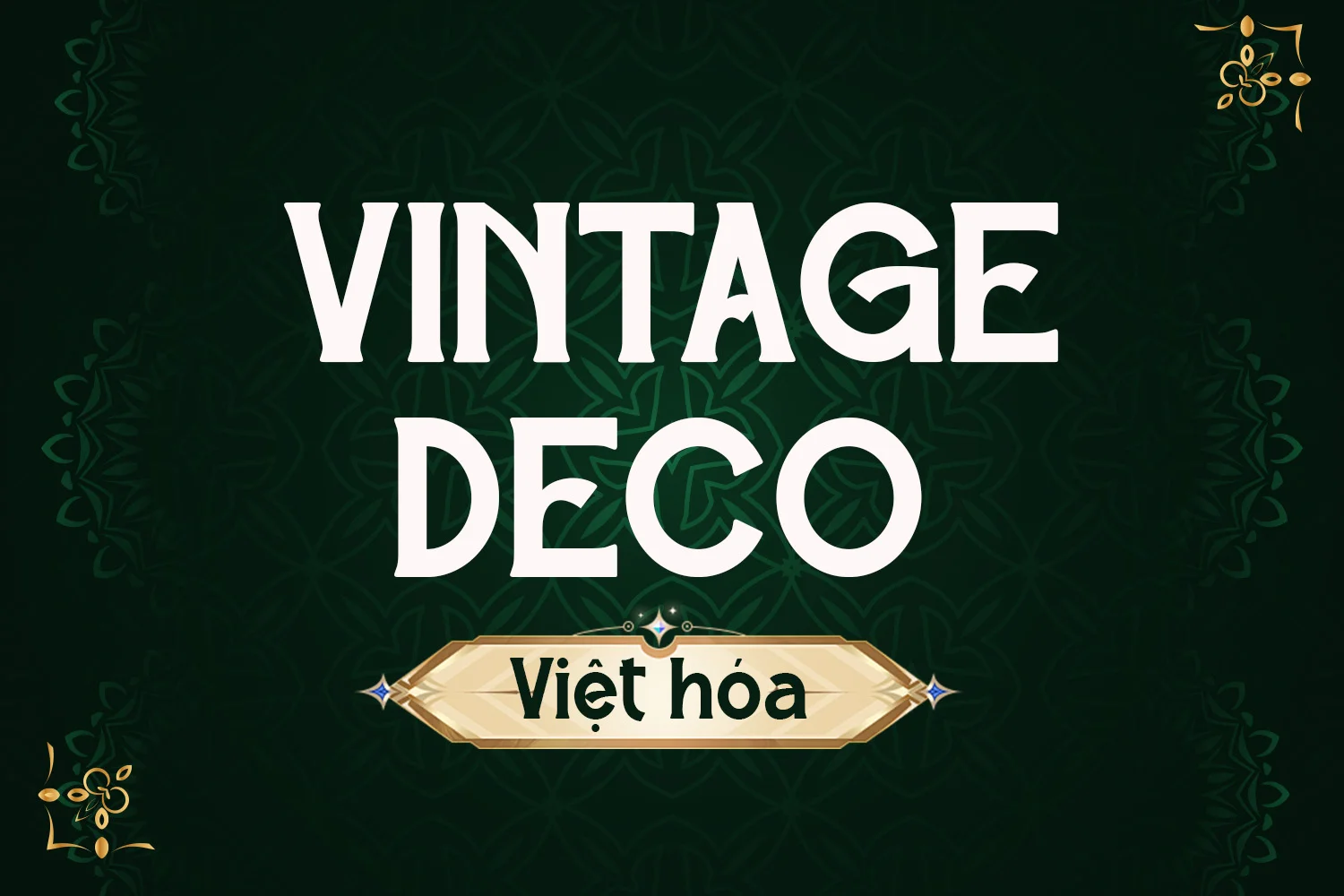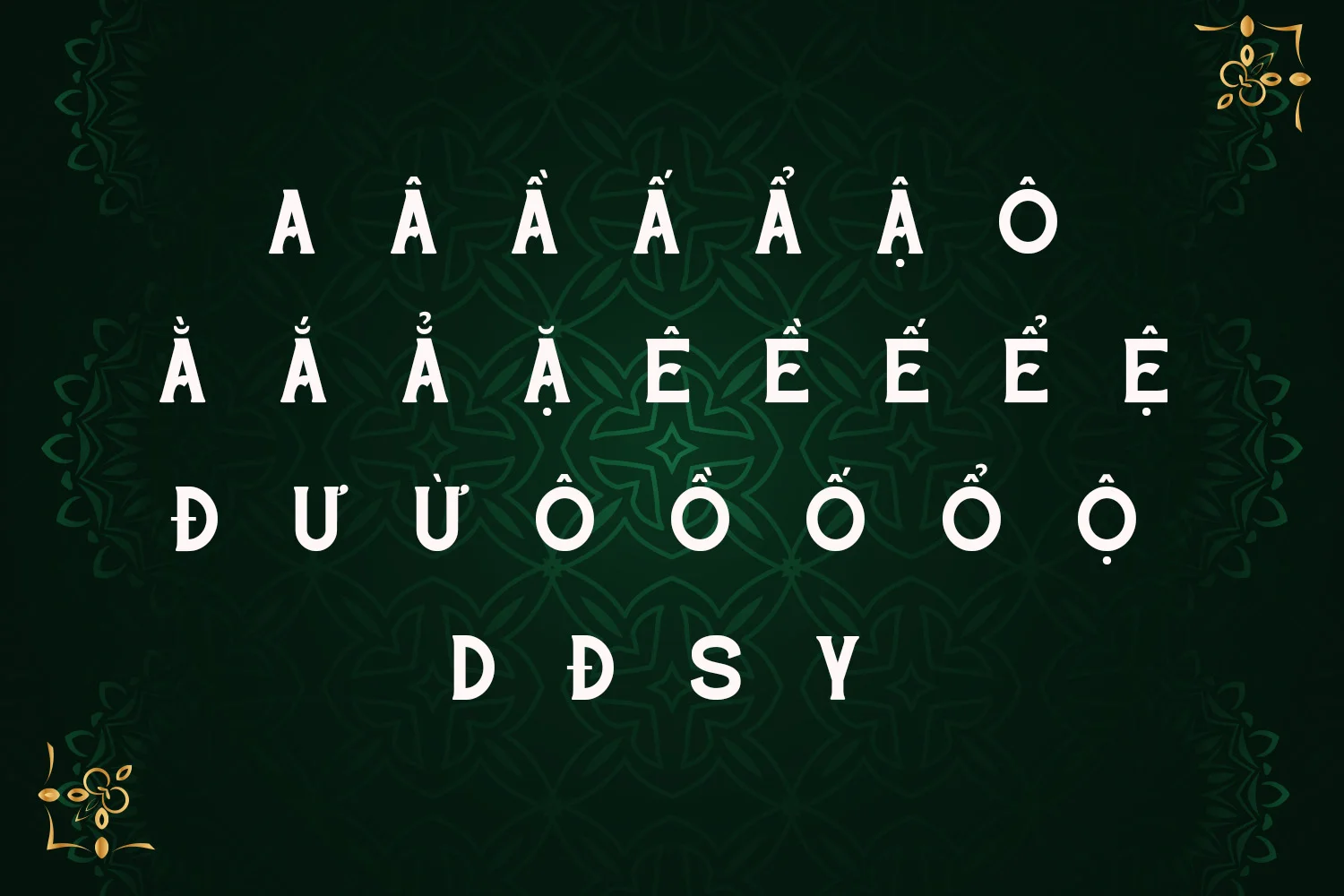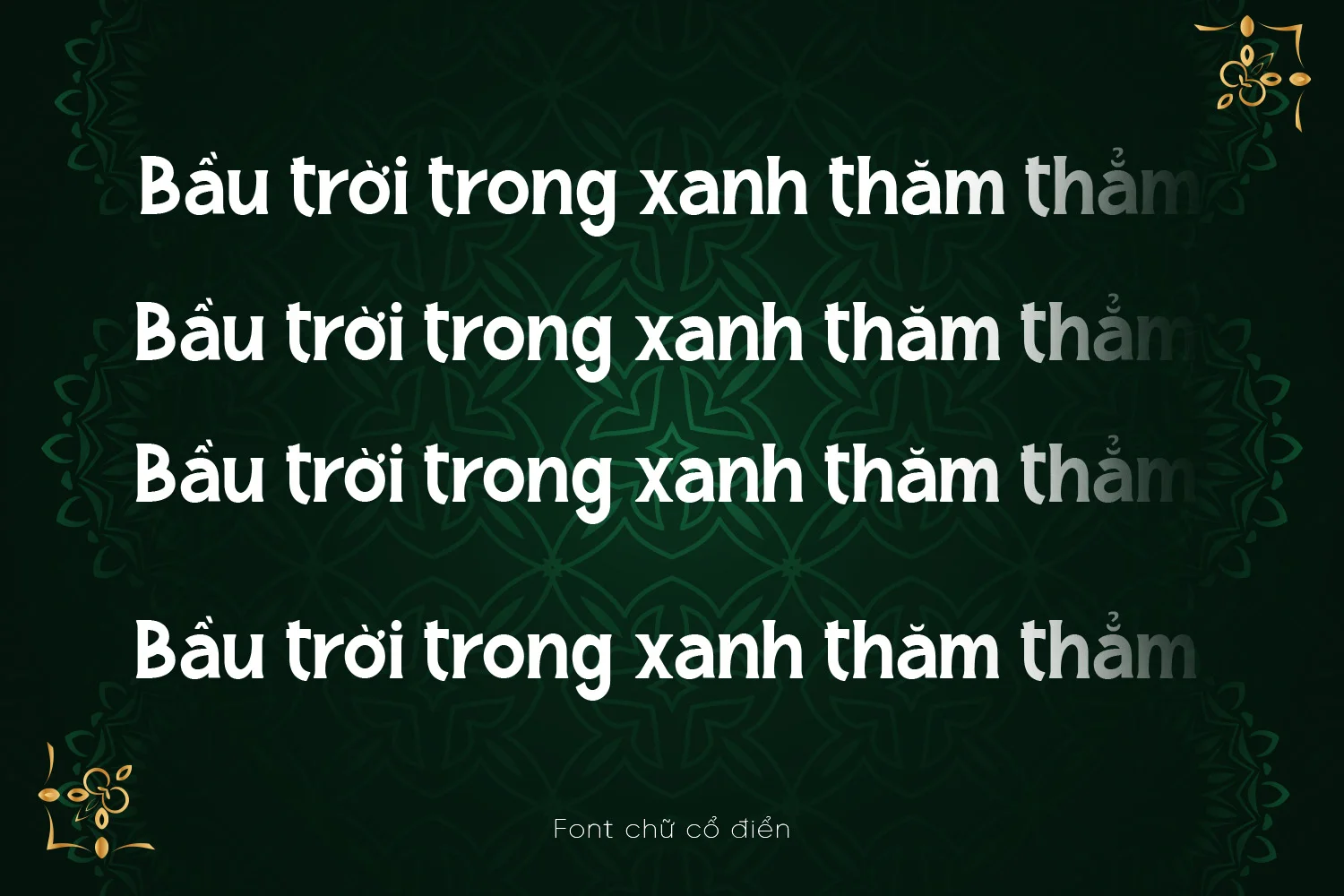
DVN Vintage Deco Việt hóa là kiểu chữ mang đậm hơi thở hoài cổ, gợi nhớ về thời đại vàng son của thiết kế Art Deco. Font sở hữu các nét cắt hình khối rõ ràng, kết hợp cùng các chi tiết trang trí tinh xảo, tạo nên cảm giác sang trọng và nổi bật. Ngoài bộ ký tự tiêu chuẩn, font còn tích hợp các ligature và ký tự thay thế độc đáo giúp bạn thoải mái sáng tạo. Bộ font hỗ trợ tiếng Việt đầy đủ và tương thích tốt trong nhiều ứng dụng thiết kế như poster phim, tiêu đề tạp chí, bìa sách vintage hay nhận diện thương hiệu cá tính. Đây là lựa chọn lý tưởng cho những ai đang tìm kiếm một phông chữ vừa đậm chất xưa, vừa chuyên nghiệp trong trình bày hiện đại.